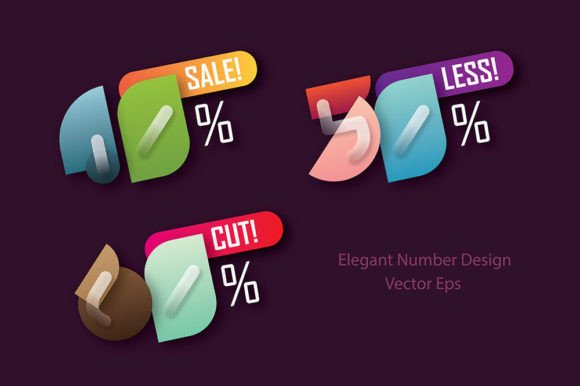
40% 50% 60% Geometric Numbers Style
การค้นหาองค์ประกอบการออกแบบที่เหมาะสมอาจเป็นเรื่องท้าทาย แต่ 40% 50% 60% Geometric Numbers Style นำเสนอคอลเลกชันที่โดดเด่นซึ่งช่วยยกระดับงานของคุณได้ทันที
สร้างขึ้นอย่างแม่นยำ 40% 50% 60% Geometric Numbers Style ให้เวกเตอร์ที่สะอาด พิมพ์ตัวอักษรที่ราบรื่น และใบอนุญาตเชิงพาณิชย์เพื่อความสบายใจ